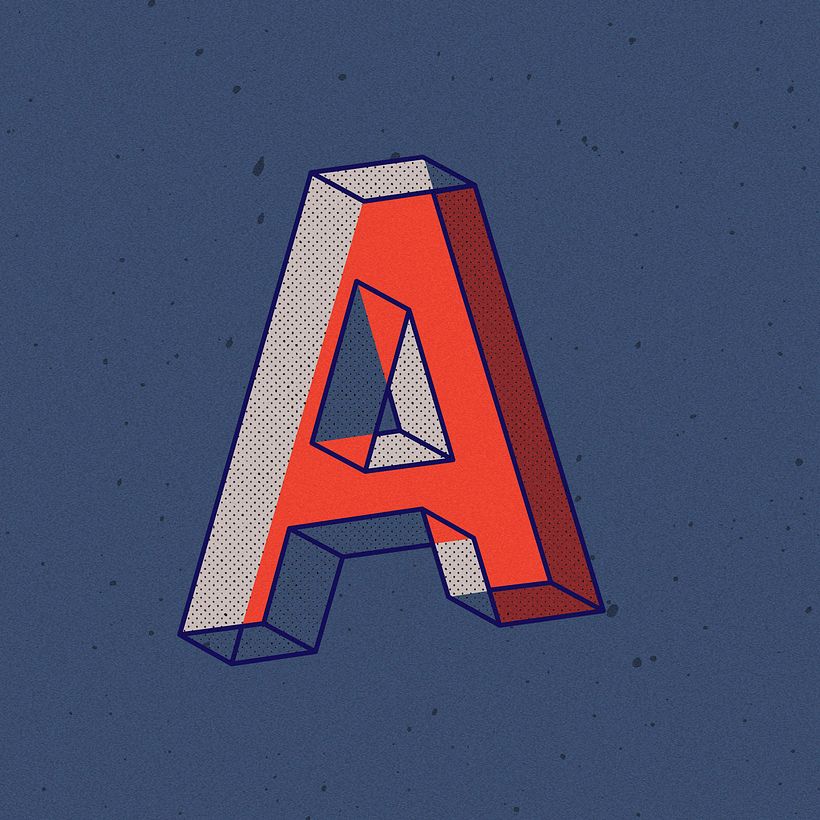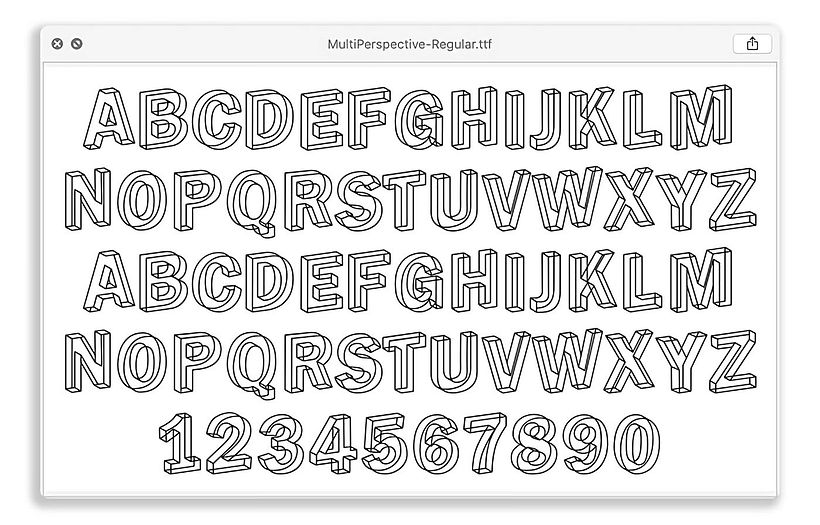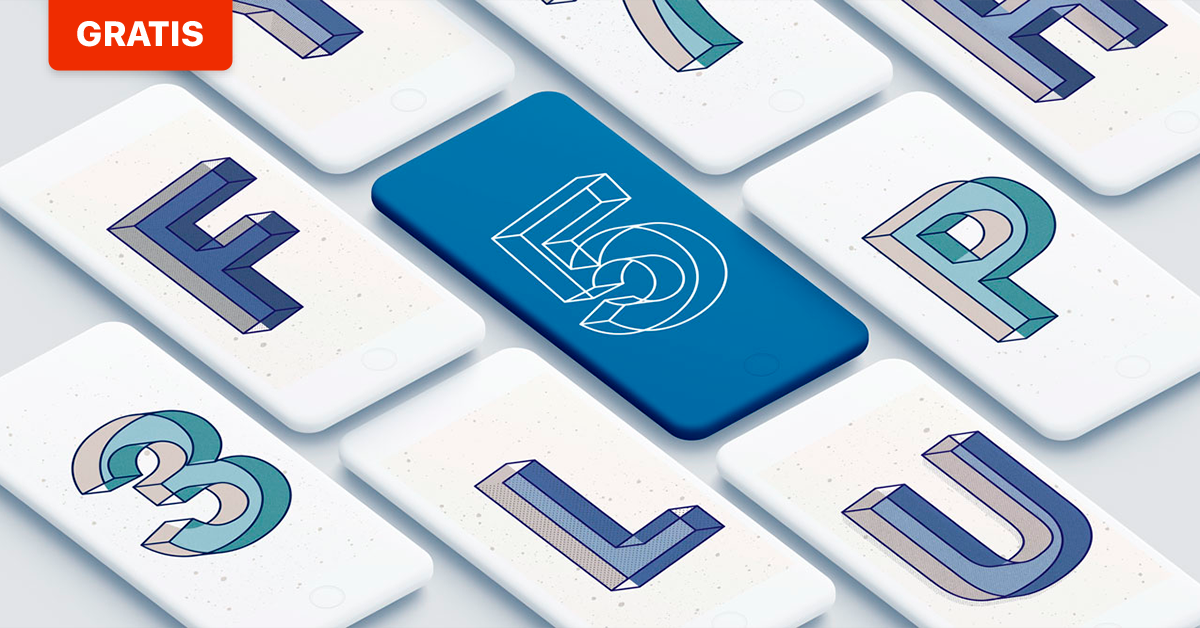
Descarga la tipografía inspirada en Escher, de Manolo Guerrero
El diseñador mexicano ha convertido en tipografía el alfabeto que diseñó para 36 days of type y lo comparte gratis
36 days of type –el reto que invita a creadores gráficos de todo el mundo a diseñar un alfabeto, creando una letra al día durante más de un mes y a publicarlo en sus perfiles de Instagram– es una oportunidad increíble para inspirarse y observar como otros resuelven un mismo brief de manera completamente diferente, adaptándolo a sus propios estilos y capacidades. Pero también es el caldo de cultivo perfecto para proyectos como esta tipografía de Manolo Guerrero (@bluetypo), el diseñador gráfico mexicano al frente de Blue Typo, que, además, comparte de manera completamente gratuita para que cualquiera pueda utilizarla.
Se trata de una tipografía experimental para cuyo diseño Guerrero quiso jugar con la perspectiva, creando una cierta reminiscencia escheriana de lo más interesante y llamativa.
Guerrero echó mano del processing "para generar la extrusión de las letras en diferentes perspectivas, para así, exportar archivos vectoriales", una técnica que explica en el curso Diseño tipográfico experimental con Processing que imparte en Domestika y que le permitió fusionar las caras vistas de las letras para crear la sensación de perspectivas encontradas.
Una vez que hubo terminado el diseño de cada letra lo trasladó a Glyphs, donde se encargó de generar el archivo en formato tif y otf para hacer de este conjunto de letras una tipografía funcional que cualquiera puede utilizar en su ordenador, en sus programas de diseño habituales.